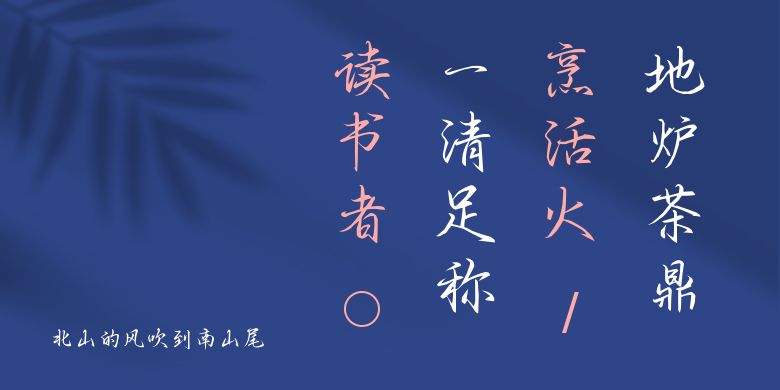
北山的风吹到南山尾
北山的风吹到南山尾,这款字体结构工整、笔画清晰,兼顾美观与易读性,适用于标题、正文、海报、包装、LOGO 等多种场景。字形优雅稳定,风格百搭耐看,适配日常排版与创意设计,让文字呈现更舒适、更具质感。北山的风吹到南山尾一笔一画,皆是细节,以均衡的比例、流畅的线条打造舒适视觉体验,字形端正大气,风格简约现代。无论是商业设计、品牌宣传还是日常排版,都能轻松驾驭,让文字更有格调与力量。北山的风吹到南山尾字体下载。